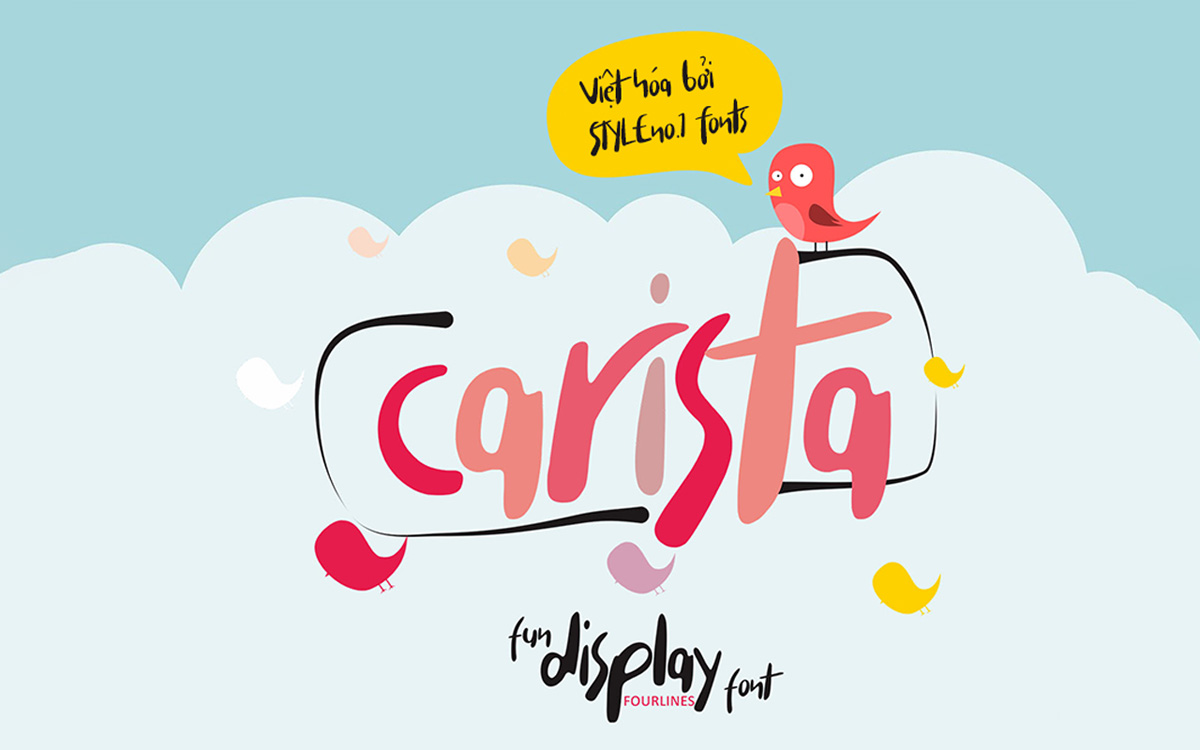
Nếu bạn đang tìm kiếm một bộ font chữ mang phong cách ngộ nghĩnh, tươi vui và đầy sức sống dành riêng cho các dự án thiết kế thiếu nhi, thì font chữ hoạt hình trẻ em vui nhộn SVN-Carista chính là sự lựa chọn hoàn hảo. Được Việt hóa tỉ mỉ và chỉn chu, bộ font này mang đến hơi thở mới mẻ, giúp mọi thông điệp trở nên sinh động và gần gũi hơn với thế giới trẻ thơ. Hãy cùng khám phá những điểm đặc sắc và ứng dụng tuyệt vời mà SVN-Carista mang lại cho cộng đồng nhà thiết kế hiện nay.
Font chữ hoạt hình trẻ em vui nhộn SVN-Carista – Giải pháp thiết kế sáng tạo và độc đáo cho các dự án thiếu nhi
Trong thế giới thiết kế đồ họa, việc lựa chọn typography phù hợp đóng vai trò quyết định đến cảm xúc của sản phẩm. Đặc biệt đối với các thiết kế hướng tới đối tượng độc giả nhỏ tuổi, font chữ không chỉ cần rõ ràng mà còn phải thể hiện được sự linh hoạt, hóm hỉnh và ngập tràn màu sắc. Bộ font chữ hoạt hình trẻ em vui nhộn SVN-Carista được sáng tạo ra nhằm đáp ứng trọn vẹn những yêu cầu khắt khe đó. Với cấu trúc nét chữ phá cách, các đường bo tròn mềm mại cùng nhịp điệu nhảy múa tự nhiên, bộ font này nhanh chóng trở thành công cụ đắc lực cho các nhà thiết kế chuyên nghiệp lẫn những người sáng tạo nội dung tự do.
1. Phong cách thiết kế hoạt hình hóm hỉnh và đậm chất ngộ nghĩnh
Điểm nổi bật đầu tiên giúp SVN-Carista thu hút mọi ánh nhìn chính là tư duy hình học tự do và đầy tính ngẫu hứng. Các chữ cái không tuân theo những quy tắc khung xương cứng nhắc của font chữ truyền thống, mà thay vào đó là sự biến tấu linh hoạt về tỷ lệ cao thấp, độ dầy mỏng và độ nghiêng nhẹ nhàng.
Cụ thể, font chữ sở hữu các đặc điểm tạo thị giác vô cùng ấn tượng:
- Đường nét bo tròn an toàn: Các góc cạnh sắc nhọn đều được xử lý bo tròn, tạo cảm giác thân thiện, an toàn và dễ chịu – đúng với tinh thần của thế giới trẻ thơ.
- Trục chữ (baseline) nhún nhảy sống động: Các ký tự không nằm trên một đường thẳng cố định mà có sự trồi sụt có tính toán, mô phỏng lại nét chữ viết tay ngây thơ của em bé hoặc chuyển động hài hước của các nhân vật hoạt hình.
- Tỷ lệ hình khối phá cách: Những khoảng hở (counter) được mở rộng, bụng chữ tròn trịa kết hợp với nét gạch ngang hơi lệch tâm tạo nên cái nhìn vừa lạ mắt vừa đáng yêu.Nhờ phong cách này, SVN-Carista giúp xóa bỏ sự khô khan của văn bản thuần túy, biến mỗi từ ngữ thành một hình ảnh minh họa sống động, dễ dàng khơi gợi trí tưởng tượng phong phú của trẻ nhỏ.
2. Hỗ trợ trọn bộ tiếng Việt chuẩn Unicode với đường nét tinh tế
Một trong những rào cản lớn nhất của các nhà thiết kế Việt Nam khi sử dụng các bộ font hoạt hình nước ngoài là lỗi font, thiếu dấu hoặc các dấu thanh (sắc, huyền, hỏi, ngã, nặng) bị lệch vị trí, làm mất đi tính thẩm mỹ tổng thể. Với font chữ hoạt hình trẻ em vui nhộn SVN-Carista, toàn bộ hệ thống ký tự tiếng Việt đã được Việt hóa một cách vô cùng công phu và chuẩn xác.
Phiên bản Việt hóa SVN cam kết mang lại trải nghiệm typography mượt mà nhất:
- Dấu thanh được thiết kế đồng bộ: Các dấu mũ (â, ê, ô), dấu móc (ư, ơ) và dấu thanh điệu được vẽ lại tỉ mỉ sao cho tỷ lệ và độ dày tương thích tuyệt đối với nét chữ gốc. Dấu không quá to gây đè chữ, cũng không quá nhỏ gây khó đọc.
- Tối ưu hóa Kerning (khoảng cách giữa các chữ): Khoảng cách giữa các chữ cái tiếng Việt có dấu được điều chỉnh chuẩn xác, tránh hiện tượng các ký tự dính vào nhau hoặc đứng quá xa nhau khi gõ các từ phức tạp.
3. Ứng dụng đa dạng trong nhiều lĩnh vực thiết kế đồ họa thiếu nhi
Không chỉ giới hạn trong một khuôn mẫu nhất định, font SVN-Carista mang tính ứng dụng vô cùng linh hoạt. Dù bạn đang thực hiện dự án truyền thông số hay sản phẩm in ấn thực tế, bộ font này đều có thể tỏa sáng và nâng tầm giá trị thẩm mỹ cho sản phẩm.
Các ứng dụng thực tế phổ biến của SVN-Carista bao gồm:
- Thiết kế sách, truyện tranh và ấn phẩm giáo dục: SVN-Carista cực kỳ lý tưởng để làm tiêu đề bìa sách truyện thiếu nhi, các trang sách tô màu, thẻ học từ vựng (flashcards) hoặc tài liệu giảng dạy mầm non. Chữ dễ nhìn giúp bé ghi nhớ mặt chữ nhanh hơn.
- Bao bì sản phẩm và đồ chơi trẻ em: Font chữ giúp các thiết kế hộp đồ chơi, bao bì bánh kẹo, nhãn chai sữa hay trang phục trẻ em trở nên nổi bật trên kệ hàng, thu hút sự chú ý của cả phụ huynh và bé.
- Quảng cáo và truyền thông sự kiện: Tạo nên những banner mừng sinh nhật, phông nền (backdrop) sự kiện trung thu, quốc tế thiếu nhi, hay các poster quảng cáo trung tâm Anh ngữ vô cùng rực rỡ và chuyên nghiệp.
- Nội dung số và Video hoạt hình: Được ứng dụng rộng rãi làm tiêu đề Video Youtube Kids, ảnh thu nhỏ (thumbnail), phụ đề hoạt hình hoặc giao diện các ứng dụng trò chơi (game mobile) dành cho trẻ em.
4. Tương thích hoàn hảo trên mọi phần mềm thiết kế và văn phòng
Font chữ hoạt hình Carista là sự lựa chọn tuyệt vời cho những ai muốn mang lại sự vui tươi và sống động cho các dự án thiết kế, làm cho mọi tác phẩm trở nên thú vị và cuốn hút.
Nhà thiết kế: Zain Fahroni
Nhà phát hành: Fourlines studio
Việt hóa: STYLEno.1 Fonts